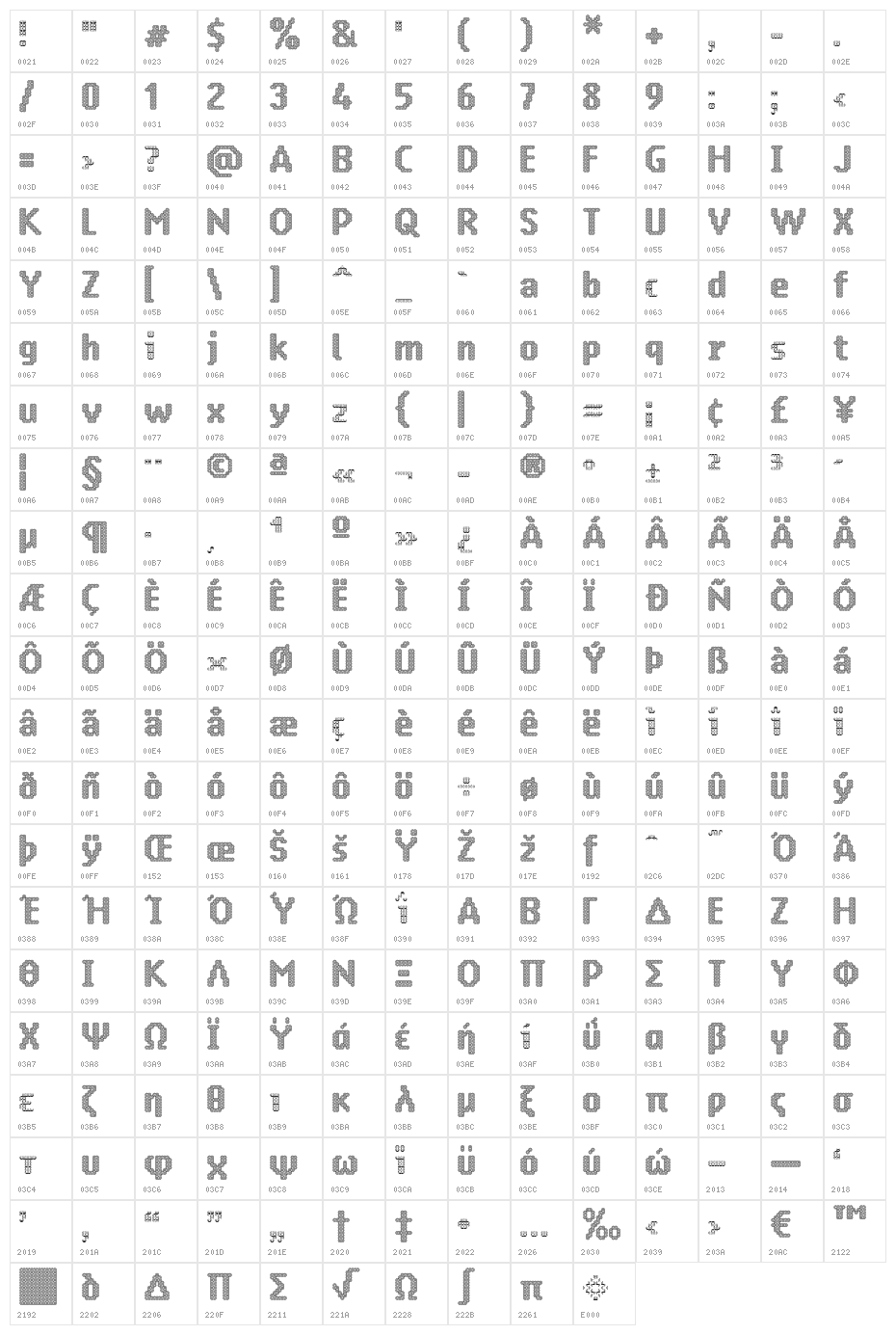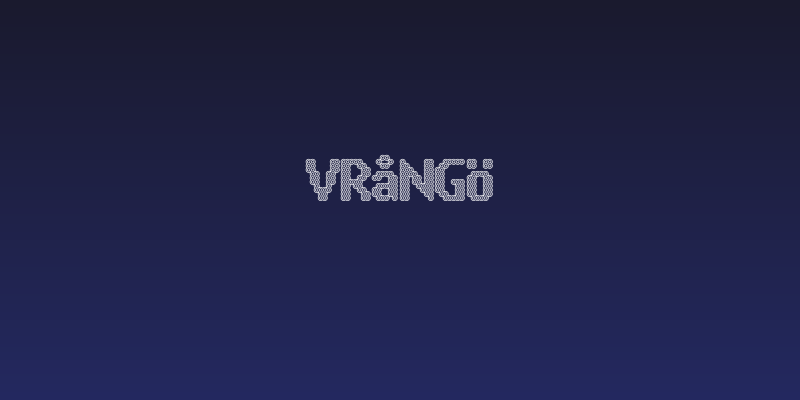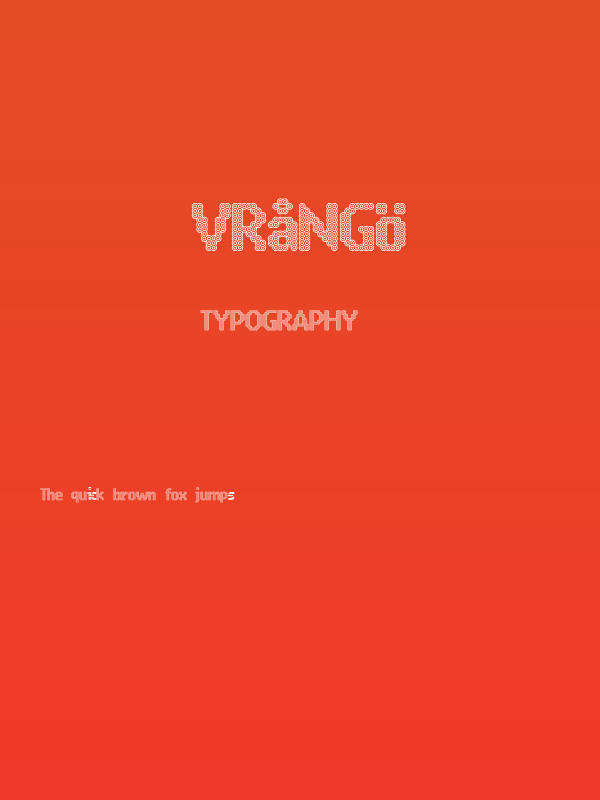
Vrångö Font
| Estilo general | Playful, Whimsical |
| Proyectos propuestos | Ideal for children's book covers, playful branding, party invitations, and creative posters. |
Vrångö